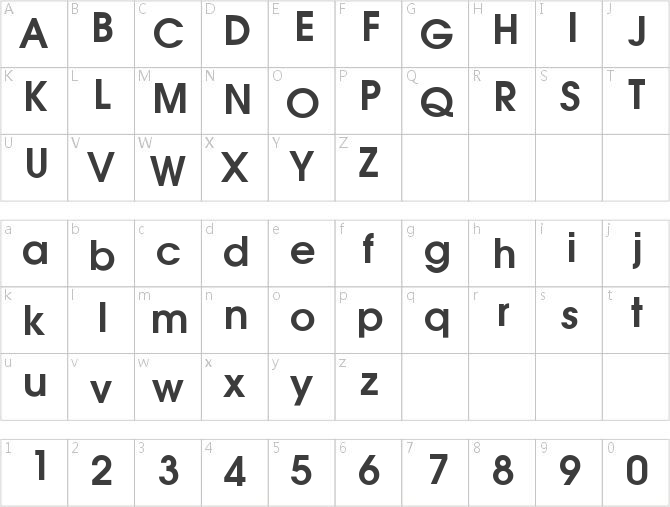
Gardenzi-Demi 詳情頁(yè)
字體名稱: Gardenz
Gardenzi-Demi
Gardenzi-Demi字體字庫(kù)是一款讓人賞心悅目、百看不厭的英文字體,適合各類廣告和產(chǎn)品包裝設(shè)計(jì)應(yīng)用,字體大小0.05MB,格式為ttf字體,上傳用戶是鄒灣灣灣灣,作者/版權(quán)方為未知